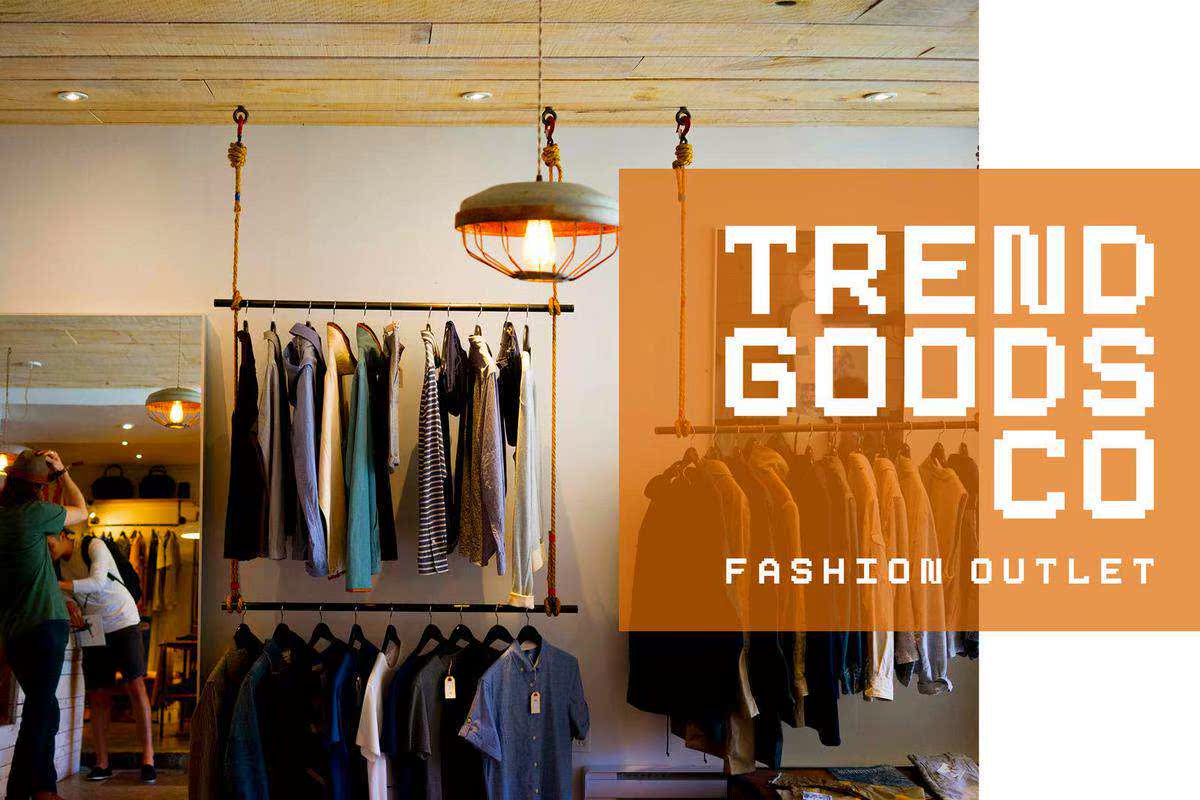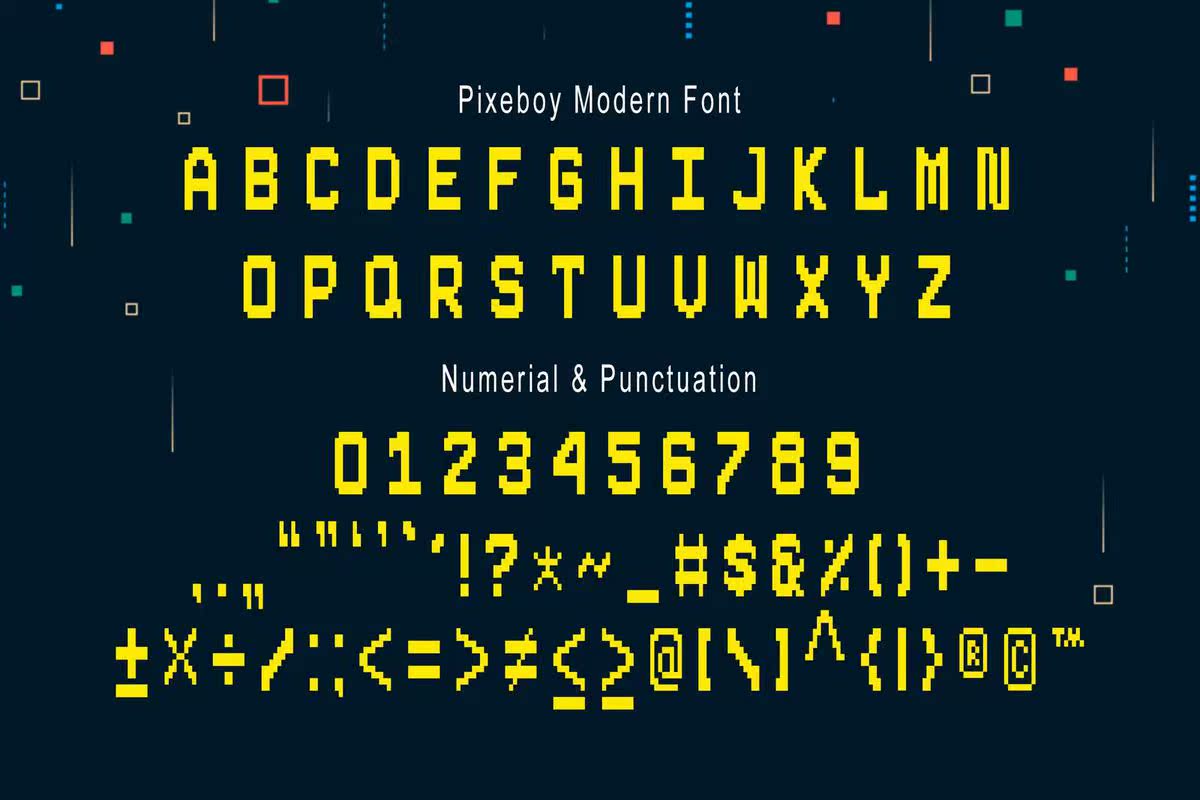
简介Pixeboy–一种现代和独特的显示字体。Pixeboy在各种显示用途方面都很出色,包括徽标、T恤、服装、报价、手写报价、产品包装、标题标题、海报、商品、社交媒体、标签、品牌和贺卡。Pixeboy是所有Caps中的一款Pixexel样式。Pixeboy是80年代128位游戏机的缩影,这使得它具有同等的技术和静态显示字体。通过其图标像素化的样式,这种原始的字体将使任何设计项目脱颖而出!简介Pixeboy–一种现代和独特的显示字体。Pixeboy在各种显示用途方面都很出色,包括徽标、T恤、服装、报价、手写报价、产品包装、标题标题、海报、商品、社交媒体、标签、品牌和贺卡。Pixeboy是所有Caps中的一款Pixexel样式。Pixeboy是80年代128位游戏机的缩影,这使得它具有同等的技术和静态显示字体。通过其图标像素化的样式,这种原始的字体将使任何设计项目脱颖而出!